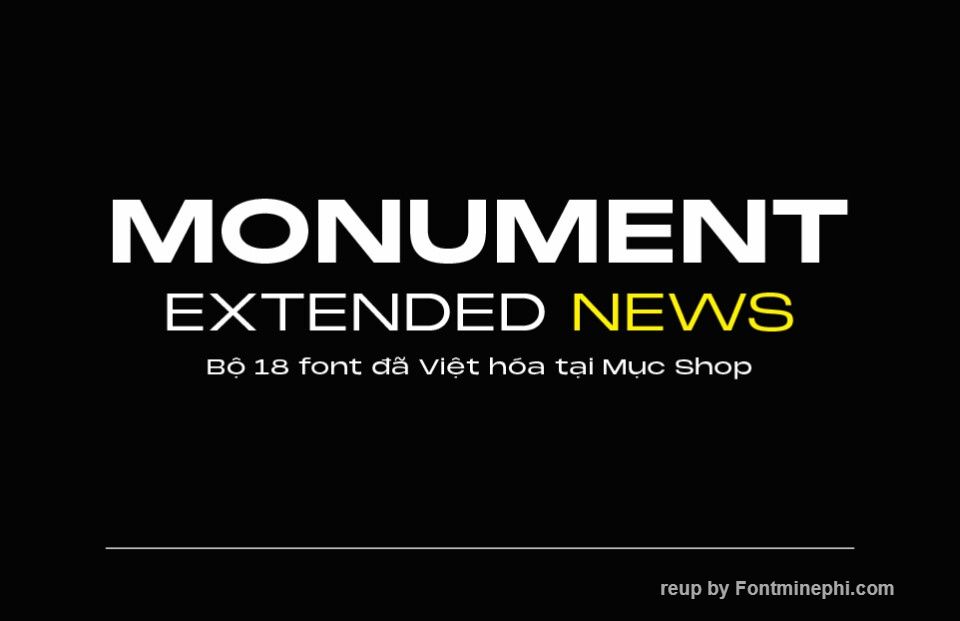
Font Việt hóa 1FTV VIP Monument Extended News là bộ phông chữ cao cấp mang phong cách sans-serif mở rộng (extended) cực kỳ hiện đại, mang đến sự mạnh mẽ, cá tính và thẩm mỹ đỉnh cao cho các thiết kế đồ họa. Bộ font đã được tinh chỉnh và Việt hóa hoàn chỉnh với hệ thống dấu tiếng Việt chuẩn Unicode, hỗ trợ tối đa cho các nhà thiết kế trong việc tạo dựng sản phẩm truyền thông ấn tượng. Hãy cùng khám phá chi tiết về bộ font VIP tuyệt vời này để nâng tầm các dự án sáng tạo của bạn.
Khám Phá Font Việt Hóa 1FTV VIP Monument Extended News – Đỉnh Cao Typography Cho Thiết Kế Hiện Đại
Trong thế giới thiết kế đồ họa đương đại, typography đóng vai trò là “linh hồn” tạo nên bản sắc và cảm xúc cho từng sản phẩm thị giác. Xu hướng sử dụng các phông chữ mở rộng (extended fonts) đang bùng nổ mạnh mẽ trong những năm gần đây, đặc biệt là ở các lĩnh vực như thời trang đường phố, công nghệ, âm nhạc và truyền thông thương hiệu. Font Việt hóa 1FTV VIP Monument Extended News chính là sự lựa chọn hoàn hảo đáp ứng trọn vẹn xu hướng này, mang lại vẻ đẹp vừa đồ sộ, vừa tinh tế cho các tác phẩm của bạn.
Phiên bản 1FTV VIP Monument Extended News được trau chuốt tỉ mỉ từ từng đường nét nét thanh, nét đậm cho đến khoảng cách giữa các ký tự (kerning). Điểm đặc biệt nhất của bản Việt hóa này là sự hài hòa tuyệt đối giữa các bộ dấu tiếng Việt và cấu trúc chữ nguyên bản. Dấu thanh được thiết kế gọn gàng, không bị đè chữ hay làm mất đi tính cân đối ngang độc đáo của phông chữ gốc, giúp trải nghiệm đọc của người xem luôn mượt mà và tự nhiên nhất.
Dù bạn đang thực hiện các dự án thiết kế thương hiệu lớn, làm biển bảng quảng cáo, sáng tạo nội dung mạng xã hội hay thiết kế bìa tạp chí cao cấp, font 1FTV VIP Monument Extended News đều thể hiện xuất sắc vai trò tạo điểm nhấn thị giác. Sự vững chãi và hiện đại của nó giúp thông điệp của bạn trở nên uy quyền, thuyết phục và thu hút ánh nhìn ngay từ giây đầu tiên.
1. Thiết Kế Extended Mở Rộng Độc Đáo Và Uy Quyền
Đặc trưng nổi bật nhất của Font Việt hóa 1FTV VIP Monument Extended News chính là tỷ lệ chữ được kéo rộng theo chiều ngang (Extended Style). Cấu trúc chữ vuông vắn, tỉ lệ khung hình rộng tạo nên cảm giác vững chắc, hiện đại và rất “tương lai” (futuristic). Khi ứng dụng vào các tiêu đề chính (Headlines), font chữ này tạo ra hiệu ứng thị giác mạnh mẽ, giúp sản phẩm truyền thông nổi bật hoàn toàn so với các thiết kế thông thường.
2. Bộ Dấu Tiếng Việt Chuẩn VIP Chuẩn Thẩm Mỹ
Nhiều font chữ nước ngoài khi gõ tiếng Việt thường gặp lỗi vỡ nét, lệch dấu hoặc dấu thanh quá to làm hỏng tổng thể. Bản Việt hóa 1FTV VIP đã giải quyết hoàn toàn vấn đề này. Các dấu huyền, sắc, hỏi, ngã, nặng cũng như các dấu mũ (â, ê, ô, ơ, ư) đều được tinh chỉnh thủ công để ăn nhập hoàn hảo với nét chữ hình học (geometric) của phông gốc, đảm bảo tính chuẩn xác và tính thẩm mỹ đỉnh cao cho tiếng Việt.
3. Độ Tương Phản Sắc Nét Và Khả Năng Hiển Thị Tuyệt Mời
Font 1FTV VIP Monument Extended News sở hữu đường nét rõ ràng, góc cạnh được xử lý dứt khoát cùng độ tương phản hợp lý. Điều này giúp bộ font giữ được độ sắc nét tối đa trên mọi nền tảng hiển thị. Từ các màn hình kỹ thuật số độ phân giải cao (Retina, OLED) cho đến các ấn phẩm in ấn kích thước lớn như Billboard, Poster hay Bao bì sản phẩm, phông chữ vẫn giữ nguyên độ rõ ràng và tính thẩm mỹ tuyệt đối.
4. Khả Năng Tương Thích Hoàn Hảo Trên Mọi Phần Mềm Thiết Kế
5. Ứng Dụng Linh Hoạt Trong Nhiều Lĩnh Vực Sáng Tạo
Không chỉ giới hạn trong một phong cách nhất định, 1FTV VIP Monument Extended News tỏ ra vô cùng đa năng. Phông chữ này là sự lựa chọn lý tưởng cho việc thiết kế Logo thương hiệu, Banner quảng cáo chương trình khuyến mãi, Bìa album âm nhạc, Thẻ bài gaming, Lookbook thời trang, hay các ấn phẩm truyền thông cho các sự kiện công nghệ và thể thao đòi hỏi sự cá tính và năng động.
Gợi Ý Phối Font Chuẩn Style Chuyên Nghiệp Với 1FTV VIP Monument Extended News
Để tạo nên một bản thiết kế có độ sâu và phân cấp thông tin (Visual Hierarchy) tốt, việc phối hợp phông chữ là vô cùng quan trọng. Dưới đây là một số công thức phối font hiệu quả khi sử dụng 1FTV VIP Monument Extended News:</p>
- Phối tương phản phong cách: Kết hợp tiêu đề 1FTV VIP Monument Extended News (mạnh mẽ, mở rộng) với phần văn bản nội dung (body text) là một font Serif cổ điển như Times New Roman hoặc Garamond để tạo sự phá cách, độc đáo cho bìa tạp chí hay poster nghệ thuật.
- Phối chuẩn Modern & Clean: Sử dụng 1FTV VIP Monument Extended News làm Title và kết hợp với các font Sans-serif tiêu chuẩn như Roboto, Montserrat, Helvetica hoặc Open Sans cho phần nội dung. Đây là công thức hoàn hảo cho thiết kế Website, Landing Page và Banner Social Media.